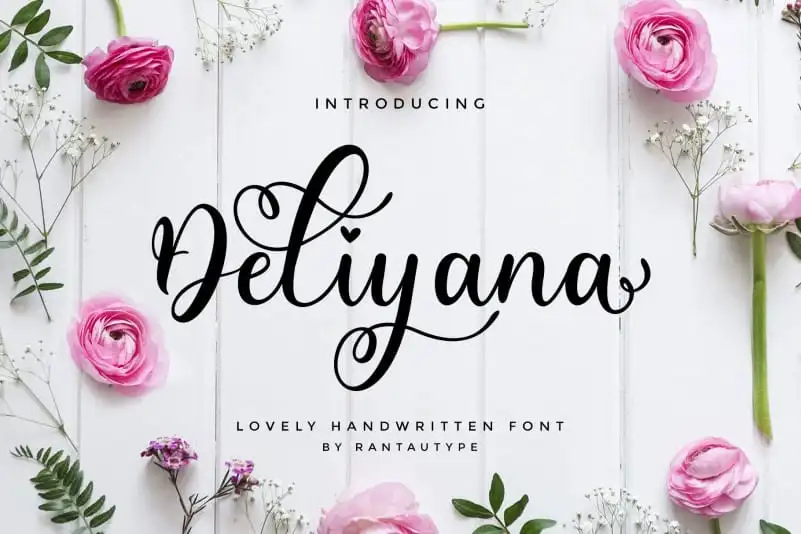
Deliyana Calligraphy Font – Download Grátis
Deliyana Calligraphy Font é uma elegante fonte script moderna, cheia de personalidade e curveis arredondados. Projetada para fornecer a aparência natural do texto escrita à mão na era digital, esta font foi criada por um designer chamado Rantautype em 99designs. Esta font é perfeita tanto para projetos profissionais quanto para aquelas ideias mais leves e gerais. Deliyana traz uma aparência moderna, feminina e girly que consegue chamar a atenção sem esforço. Ela é fácil de usar e permite ao designer expressar suas criações de um modo único. Deliyana Calligraphy Font torna-se o escolha perfeita para projetos variados como design de marca (watermark em fotografias, assinaturas ou logomarcas), design de cartões de visita, capas de álbuns e mesmo frases de citação. Ela transformará seu trabalho num nível mais alto! Com sua aparência única e versátil, Deliyana é uma excelente opção para quem busca dar um toque especial a seus projetos em fotografia, design gráfico ou qualquer outro campo que precise de um texto criativo e profissional.